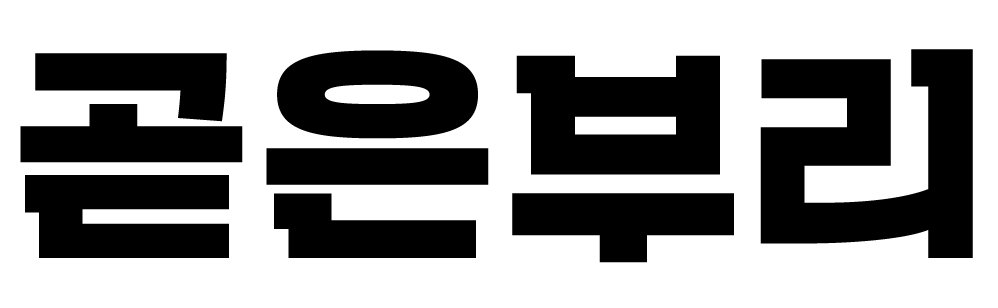
산돌 '곧은부리'는 무겁고 각이 진 세리프 즉, 슬랩세리프의 양식을 한글 디자인에 적용하여 묵직하게 강한 인상으로 표현한 서체이다.
곧은부리는 정방형의 굵은 세리프가 비슷한 굵기의 기둥과 직각으로 만나는 '이집션(Egyptian)' 양식이 적용되었으며, 큰 주목을 끌고 강한 시각적 인상을 줄 수 있도록 디자인 되었다.